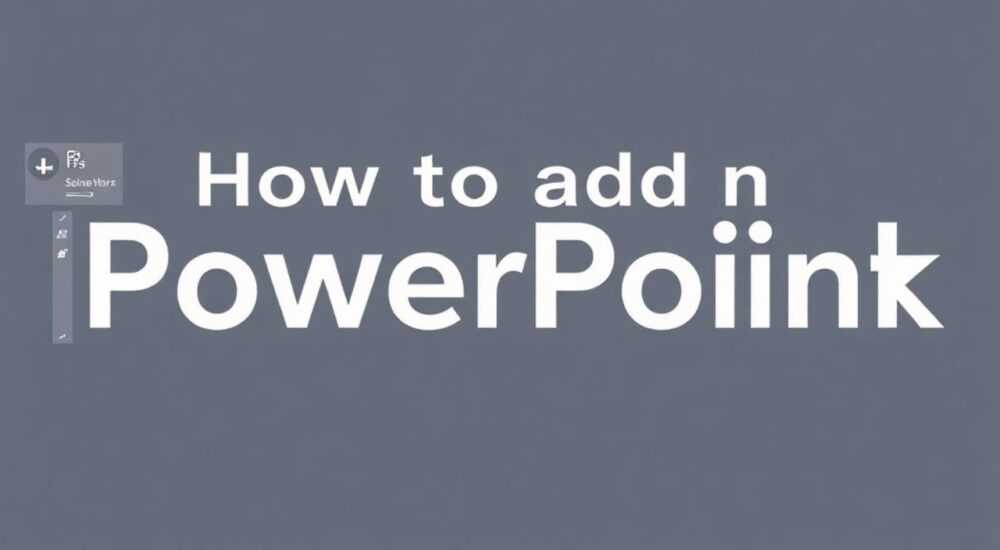
Как поставить шрифт в powerpoint
Работа с шрифтами в PowerPoint может стать настоящим вызовом, особенно когда презентация требует особенного стиля или корпоративного оформления. Задумывались ли вы, почему иногда нужный шрифт просто не отображается на слайдах? Или как сделать так, чтобы ваша презентация выглядела одинаково хорошо на любом компьютере? От правильного выбора и установки шрифтов зависит не только внешний вид презентации, но и её восприятие аудиторией. В этой статье мы подробно разберём все аспекты работы со шрифтами в PowerPoint, от базовой установки до продвинутых техник оптимизации.
Основные способы добавления шрифтов в PowerPoint
Существует несколько методов установки шрифтов, которые можно использовать в PowerPoint. Рассмотрим каждый из них более детально:
- Через системные настройки Windows
- Прямая установка через PowerPoint
- Использование облачных шрифтов Microsoft 365
Первый способ считается наиболее универсальным, так как установленные через системные настройки шрифты становятся доступны во всех приложениях. Для этого нужно скачать файл шрифта (обычно формата .ttf или .otf), щёлкнуть по нему правой кнопкой мыши и выбрать «Установить». Важно помнить, что для установки шрифтов в системные папки могут потребоваться права администратора.
Второй метод предполагает использование встроенных возможностей PowerPoint. При попытке применить незнакомый шрифт программа предложит его установку. Этот способ особенно удобен, когда нужно быстро добавить конкретный шрифт непосредственно из интерфейса программы. Однако стоит учитывать, что таким образом шрифт становится доступным только для текущего пользователя.
Третий вариант — использование облачных шрифтов через подписку Microsoft 365. Это современное решение позволяет работать с обширной библиотекой шрифтов без необходимости их локальной установки. Достаточно выбрать нужный шрифт из коллекции, и он автоматически станет доступен во всех устройствах пользователя.
Пошаговые инструкции по установке шрифтов
Разберём процесс установки шрифтов через системные настройки Windows более подробно. Сначала необходимо найти и скачать нужный шрифт. Лучше всего использовать проверенные ресурсы, такие как Google Fonts или официальные сайты производителей шрифтов. После загрузки выполните следующие шаги:
- Откройте Панель управления
- Перейдите в раздел «Шрифты»
- Нажмите «Установить новый шрифт»
- Выберите скачанный файл и подтвердите установку
Альтернативный метод предполагает простое перетаскивание файла шрифта в папку «Fonts» через проводник Windows. Этот способ работает быстрее, но требует более высоких привилегий пользователя.
Для пользователей Mac процесс немного отличается. Шрифты устанавливаются через приложение «Книга шрифтов». Просто дважды кликните по файлу шрифта и нажмите «Установить». Система автоматически разместит шрифт в соответствующей директории.
Сравнительная характеристика различных методов установки шрифтов
Метод установки |
Совместимость |
Системная установка |
Глобальная доступность |
Требует прав администратора |
Windows/Mac |
Через PowerPoint |
Быстрая установка |
Ограниченная доступность |
Microsoft 365 |
Облачные шрифты |
Автоматическая синхронизация |
Требует подписку |
Microsoft 365 |
Каждый метод имеет свои особенности использования. Системная установка обеспечивает максимальную совместимость, но может быть ограничена политиками безопасности организации. Установка через PowerPoint удобна для единичных случаев, но не решает проблему совместной работы над презентацией. Облачные шрифты предлагают современное решение, однако зависят от наличия активной подписки и стабильного интернет-соединения.
Практические рекомендации и частые ошибки
В своей практике я часто сталкиваюсь с типичными ошибками пользователей при работе со шрифтами в PowerPoint. Вот основные проблемы и их решения:
- Шрифт не отображается корректно — проверьте наличие всех необходимых символов в наборе
- Проблемы с кириллицей — используйте шрифты с полной поддержкой Unicode
- Искажение текста при переносе — внедряйте шрифты в файл презентации
Важно помнить, что не все шрифты подходят для презентаций. Например, слишком тонкие или декоративные шрифты плохо читаются с расстояния. Оптимальный размер шрифта для основного текста — от 18pt до 24pt.
Яна Ковалёва, дизайнер презентаций с 10-летним опытом работы в крупных международных компаниях, делится своими наблюдениями: «Многие клиенты недооценивают важность правильного выбора шрифтов. Однажды мне пришлось переделывать всю презентацию за ночь, потому что выбранный шрифт оказался недоступен на компьютере заказчика.»
По словам эксперта, ключевые моменты при работе со шрифтами:
«Всегда проверяйте наличие запасного варианта шрифта, сохраняйте презентацию в формате PDF для демонстрации, и никогда не используйте более двух-трёх различных шрифтов в одной презентации.»
Часто задаваемые вопросы о шрифтах в PowerPoint
- Как сделать шрифт доступным на всех устройствах?